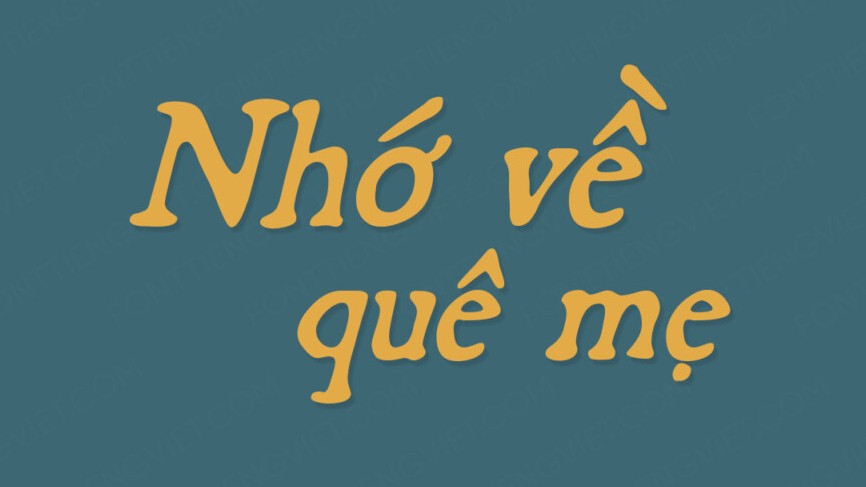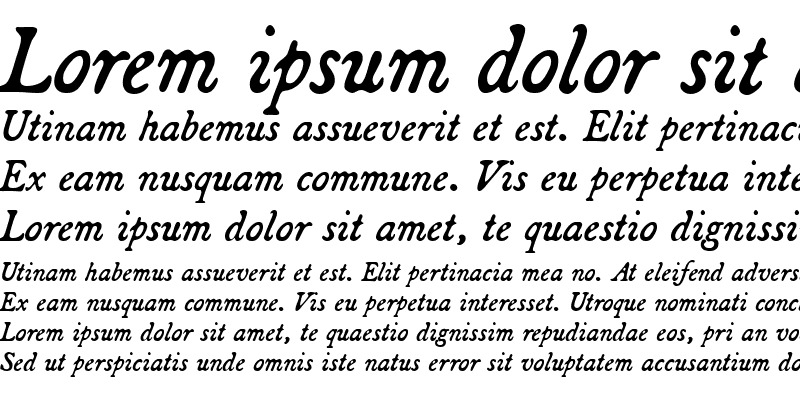
NVN Broadsheet font là gì?
NVN Broadsheet là phông chữ thuộc dòng Serif mang phong cách cổ điển, vững chãi và vô cùng trang trọng. Đặc trưng của font chữ Broadsheet là độ tương phản nét thanh đậm rõ rệt cùng đường chân chữ mạnh mẽ, gợi nhắc đến phong cách trình bày của các tờ báo lớn và tạp chí kinh tế danh tiếng toàn cầu.
Ưu điểm vượt trội của bộ phông này là khả năng hiển thị cực tốt trên các loại giấy nhám như giấy Kraft hay giấy Mỹ thuật có gân. Bản NVN Broadsheet font Việt hóa đã được căn chỉnh kerning tiếng Việt hoàn hảo, đảm bảo các đoạn văn bản dài luôn thoáng đạt và cực kỳ dễ đọc.
Lưu ý: NVN Broadsheet mang phong cách trang trọng. Bạn nên sử dụng phông chữ này cho các tiêu đề chính trên hộp cứng để tạo cảm giác quyền uy cho thương hiệu.
NVN Broadsheet font được ứng dụng như thế nào trong thiết kế và sản xuất?
Vẻ đẹp vững chãi của font chữ Broadsheet giúp nâng tầm giá trị cho mọi sản phẩm, cụ thể:
- Sản xuất hồ sơ năng lực và Catalogue: Broadsheet giúp các thông tin chi tiết về doanh nghiệp trở nên chuyên nghiệp, tạo niềm tin cho khách hàng và nhà đầu tư.
- Thiết kế bao bì hộp yến sào hạng sang: Chữ Broadsheet in ép kim nhũ bạc trên nền hộp tối màu tạo hiệu ứng thị giác đẳng cấp và đầy quyền uy cho set ấn phẩm đối ngoại.
- In ấn báo cáo thường niên tập đoàn: Phông chữ này gợi nhắc về sự chính xác và chất lượng vượt trội, giúp doanh nghiệp khẳng định vị thế trên thị trường.
- Trang trí bộ ấm chén sứ tri ân đối tác: Hình ảnh chữ nghệ thuật dùng phông Broadsheet in nung men sứ tạo nên bộ sản phẩm lưu niệm sang trọng và bền bỉ.
Sử dụng font chữ NVN Broadsheet cần lưu ý gì?
Để bản in sử dụng font Broadsheet đạt độ sắc sảo cao, designer cần quan tâm:
- Kiểm soát độ dày đường chân (Serif): Khi in kích thước siêu nhỏ trên tem nhãn, các đường chân chữ Serif dễ bị dính vào nhau. Bạn nên tăng kerning để đảm bảo khả năng đọc.
- Hạn chế in trên vải thô: Với cấu trúc nét thanh mảnh, Broadsheet không phù hợp để in lụa trên vải bố hay vải canvas dày vì dễ bị mất nét chi tiết.
- Lựa chọn hệ màu CMYK chuẩn: Luôn thiết lập mã màu chuẩn in ấn để màu chữ Broadsheet sau in trung thực với thiết kế bản máy.